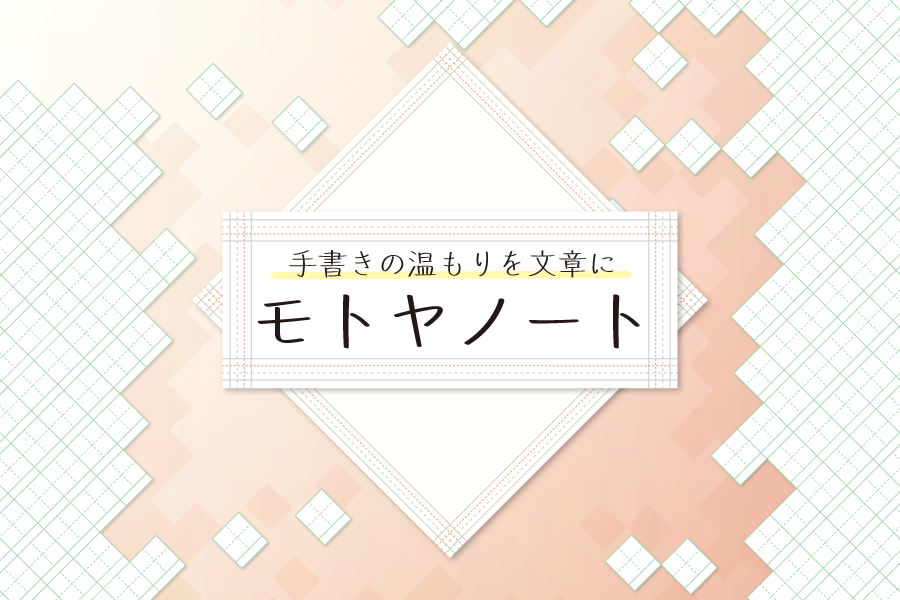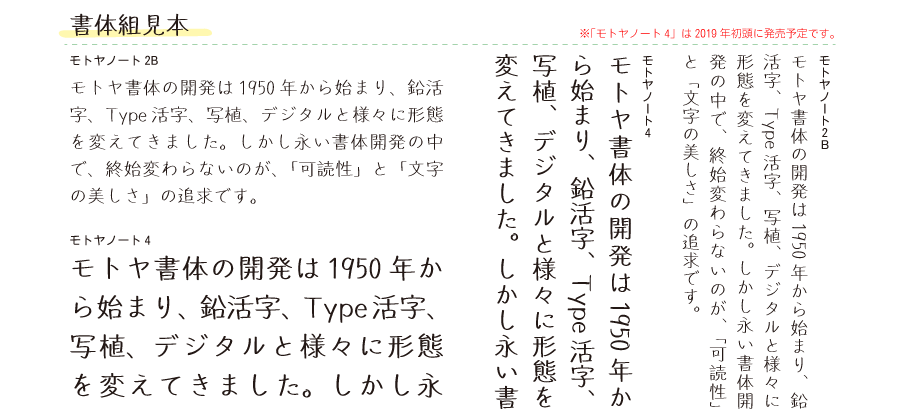
モトヤが手書きの温もりを感じる新書体「モトヤノート」を発表
モトヤが新書体として、モトヤでは初となる手書きのエッセンスを持った書体「モトヤノート」を2018年7月27日に発表した。
モトヤノートは、ペンを走らせたときに生じる線の太さが不揃いになる点やフリーハンドならではの特徴として、曲線的な表現が多くなる点、その他、横線を書き終え、そのまま縦棒を書き出すときにできる若干の隙間といった「人間らしさ」を強調した書体。
モトヤノート書体見本(2B/4)
モトヤノートは人間らしい温かみのある手書き書体で、紙媒体と相性も良く、誰かへ宛てるメッセージや短いコメントにも、優しさや温かみを表現できる。